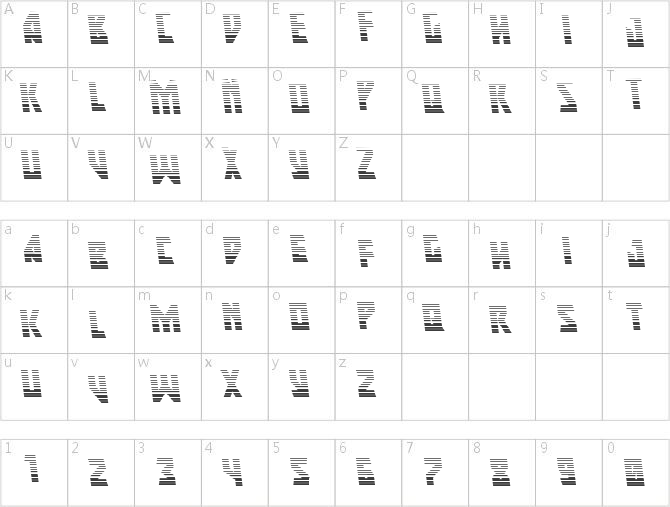
Major Force Gradient Leftalic
Major Force Gradient Leftalic介紹
Major Force Gradient Leftalic字體字庫是一款讓人賞心悅目、百看不厭的英文字體,適合各類廣告和產品包裝設計應用,字體大小0.06MB,格式為ttf字體,上傳用戶是青檸檬,作者/版權方為未知